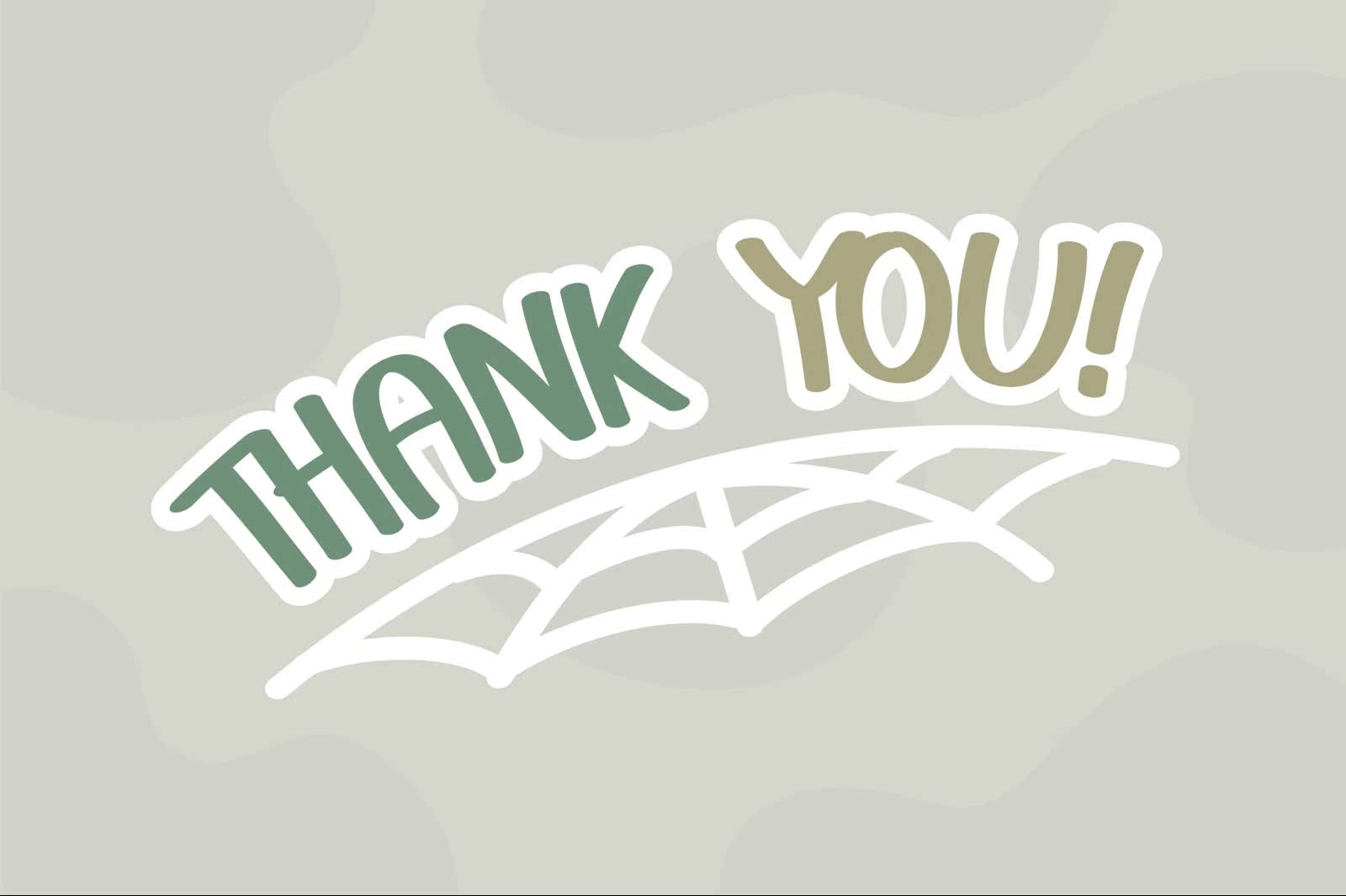
ScaryCandy是万圣节最可爱、最糟糕的服装。它的自然风格和独特风格使得它越来越多地融入到大量的设计中,并将插图和文字捆绑在一起。ScaryCandy是名片、印花T恤、时尚艺术品或只是玩乐的完美之选。万圣节的所有节日都是使用该产品的完美之选!ScaryCandy是万圣节最可爱、最糟糕的服装。它的自然风格和独特风格使得它越来越多地融入到大量的设计中,并将插图和文字捆绑在一起。ScaryCandy是名片、印花T恤、时尚艺术品或只是玩乐的完美之选。万圣节的所有节日都是使用该产品的完美之选!